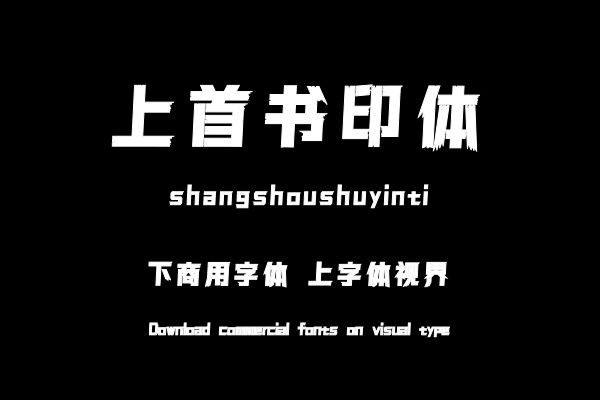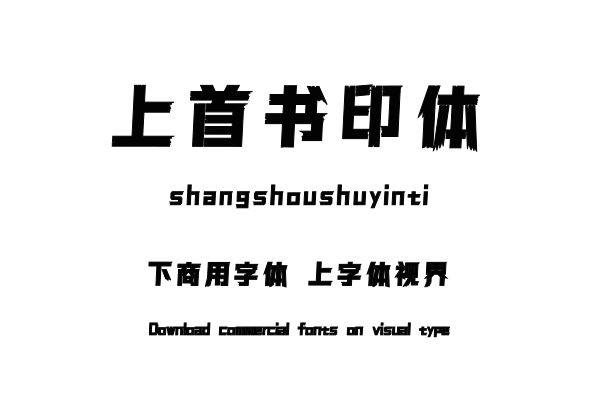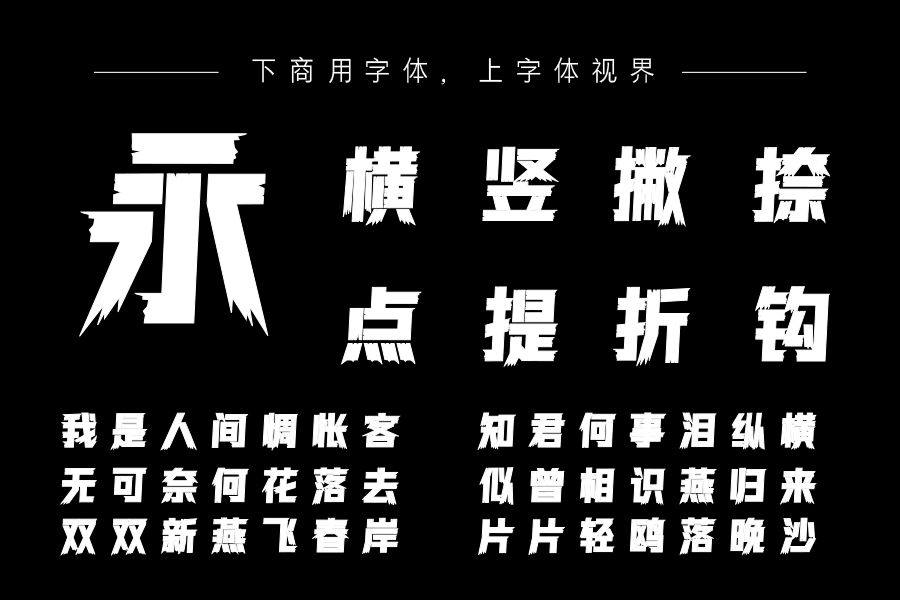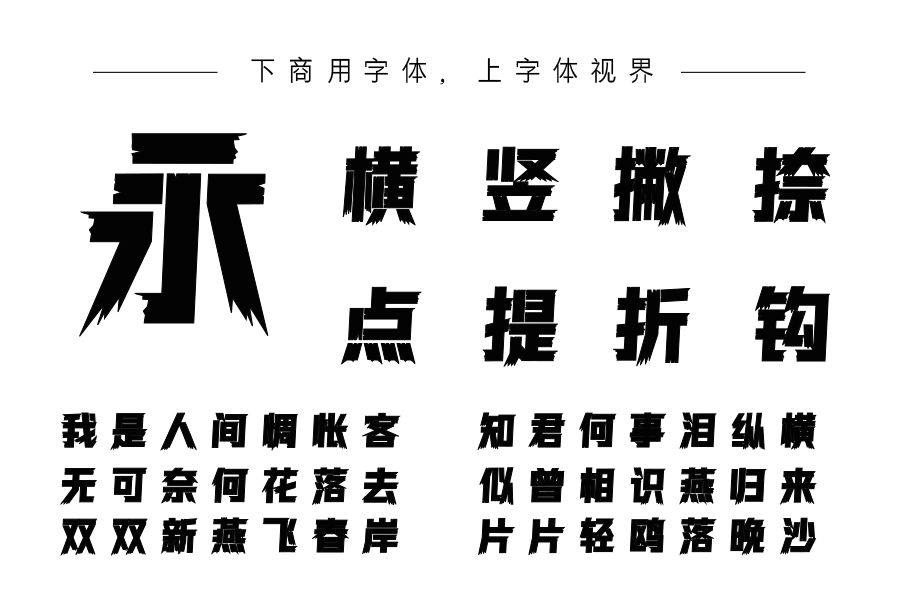
字体整体方正、简洁朴素。笔画结构进行了截断倾斜处理,字体整体给人以生动、坚毅的感觉。购买须知:“下载服务费”与“字体VIP”所获得字体 仅用于个人非商用, 商用请联系付费授权。本字体为电脑用字,手机没有root权限不支持直接手机换字(手机如何root,请自行百度搜索教程)。购买前请先 了解清楚后再付款 ,字体为虚拟产品无法回收 一旦购买不支持退款。